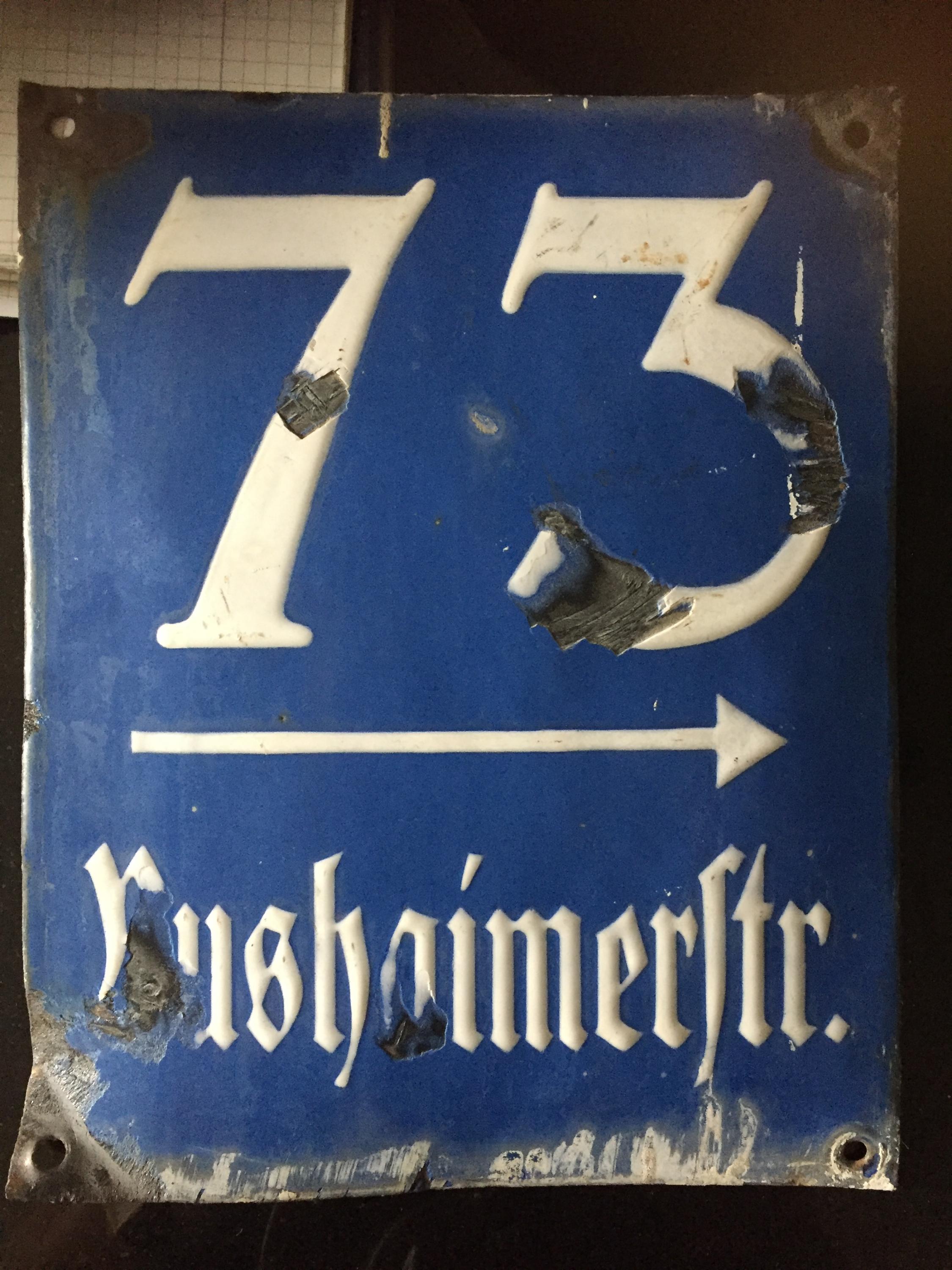
Hausnummernschild von 1937 - welche Schrift ist das?
Unser Hausnummernschild ist stark beschädigt worden und muss neu angefertigt werden, dazu muss ich aber die Schriftart wissen. Meine bisherigen Recherchen haben ergeben, dass es in Richtung Koch Fette Deutsche Schrift gehen könnte.
Kennt sich vielleicht jemand besser aus mit Frakturschriften? Das Schild stammt aus München aus der Zeit 1936/37.
Das Problem bei Emailschildern, dass hier oft individuell gezeichnete Haus-Schriftvorlagen der Emailierbetriebe verwendet wurden, die angepasst an die speziellen Bedürfnisse der Emailschilder-Herstellung entworfen wurden. Das die Emailierschablone handgefertigt war siehtb man schon an den leicht unterschiedlichen r in ...meister... und in ...ſtr.
Die Koch ist es jedenfalls nicht, und ich habe den Katalog meis Kollegen Gerhard Helzel mal duchgeschaut, der immerhin 419 verschiedene Frakturschriften anbietet - diese hier aber eben nicht:
Ebensowenig fand ich sie im Angebot von Ulrich Zeidler:
konnte ich sie beim zugegeben raschen durchsehen nicht entdecken.
PS: Gibt es in der Gegend eventuell weitere Schilder in besserem Zustand, sodass man auch z.B. das B richtig sehen, und so eventuell auch besser nachzeichnen kann, denn ich fürchte, das wird der einzige Weg zum neuen Schild sein.
das ist schneller nachgezeichnet als dass man mühsam alte schriften sucht. lediglich das korrekte endformat des schildes muss man wissen sowie den ersten buchstaben dieser straße. dann geht das.
Es stellt sich ja immer die Frage Rushaimerstr. oder Rushaimer Str.
Heute beim Spazierengehen habe ich mal auf die Schilder in Laim geachtet. Hier ein paar Beispiele. Die Qualität ist zum Teil schlecht, weil meine Kinder so schnell mit dem Roller waren ...
Ich sehe keine Ähnlichkeit zum Rushaimerstraße-Schild. Auch untereinander nicht bei den Hausnummern-Schildern. Bei der Brosamerstraße und Veit-Stoß-Straße handelt es sich um Straßenschilder der Stadt, die an Häusern angebracht sind.
@angel-35 muß wohl selbst nochmal in der Rushaimerstraße spähen, um ähnliche Schilder zu finden.